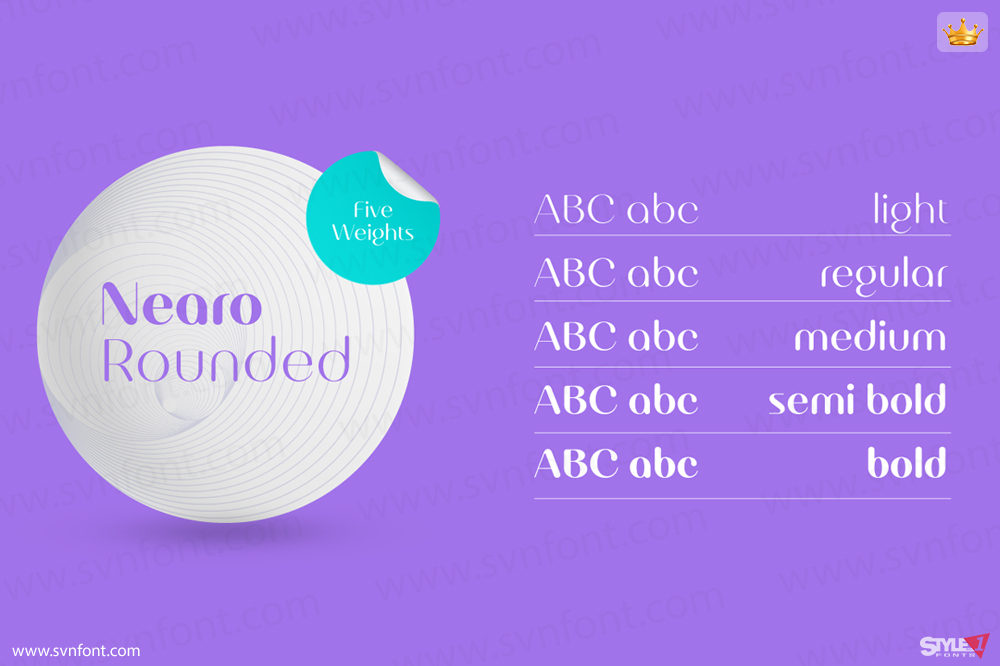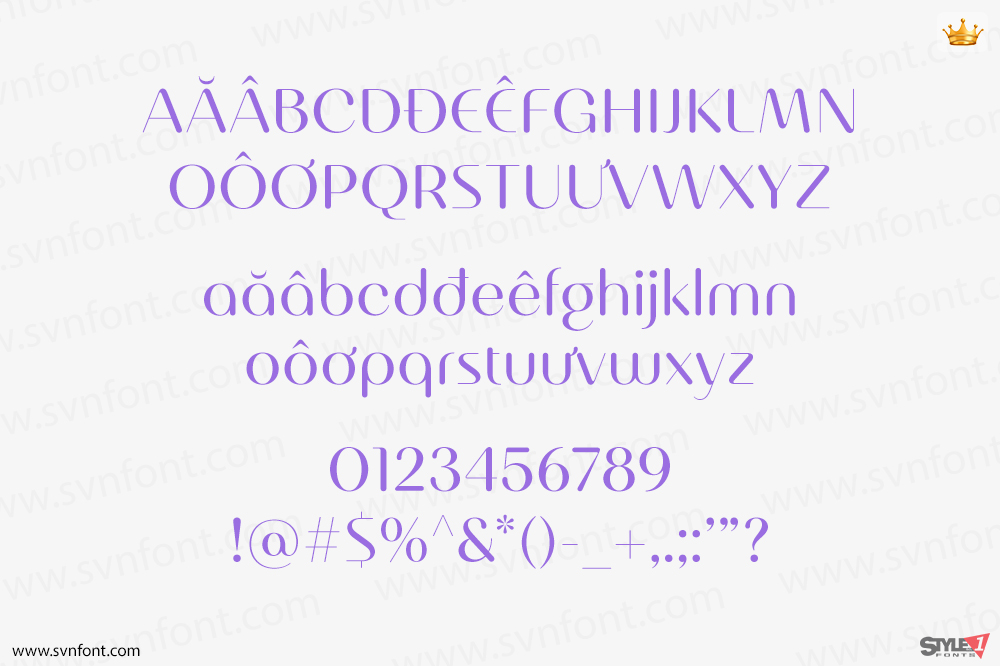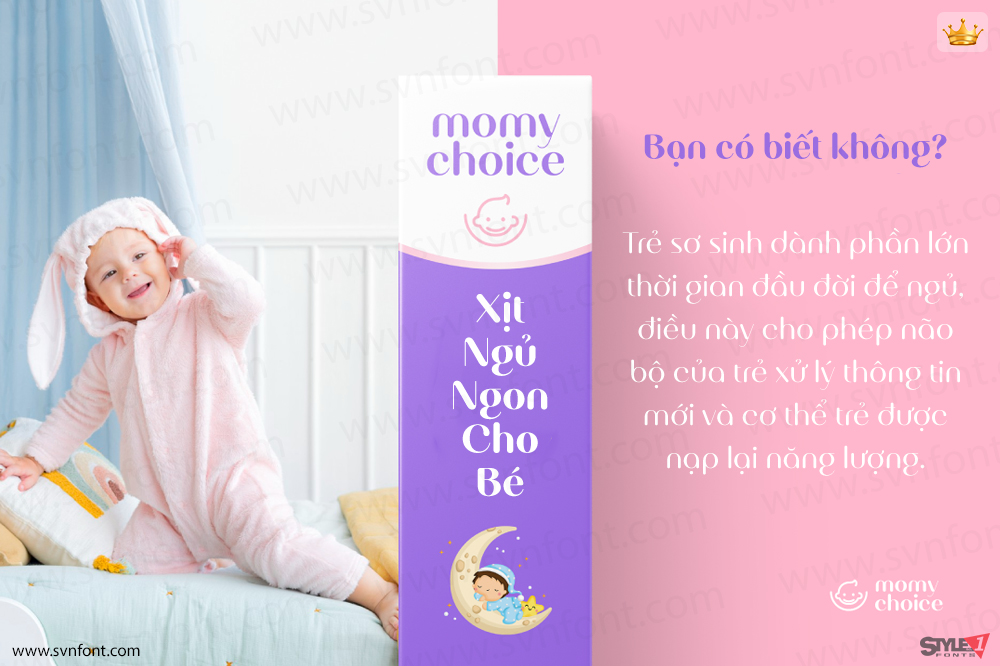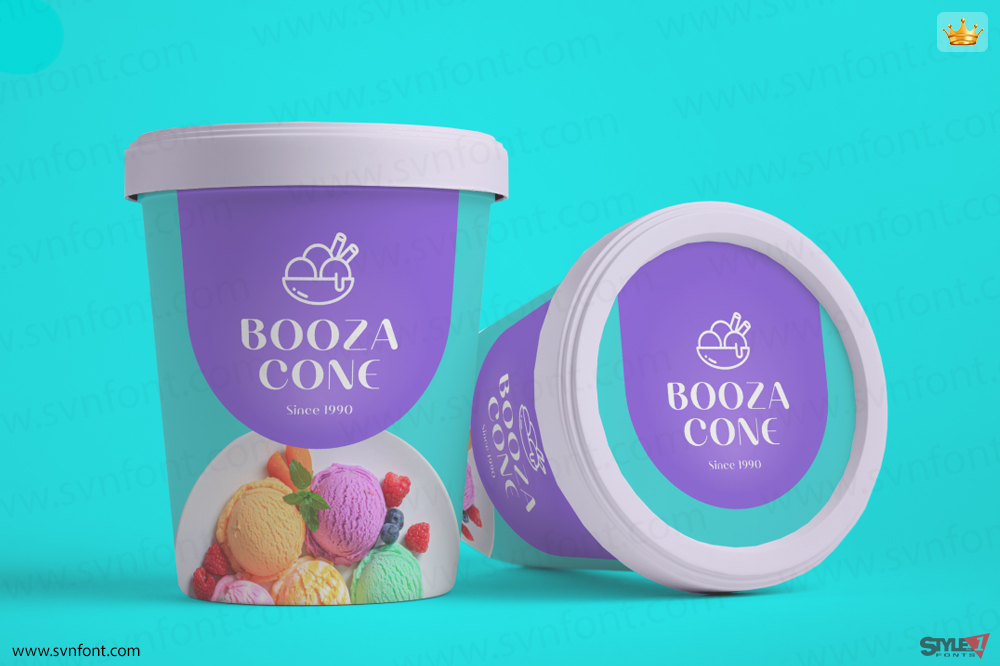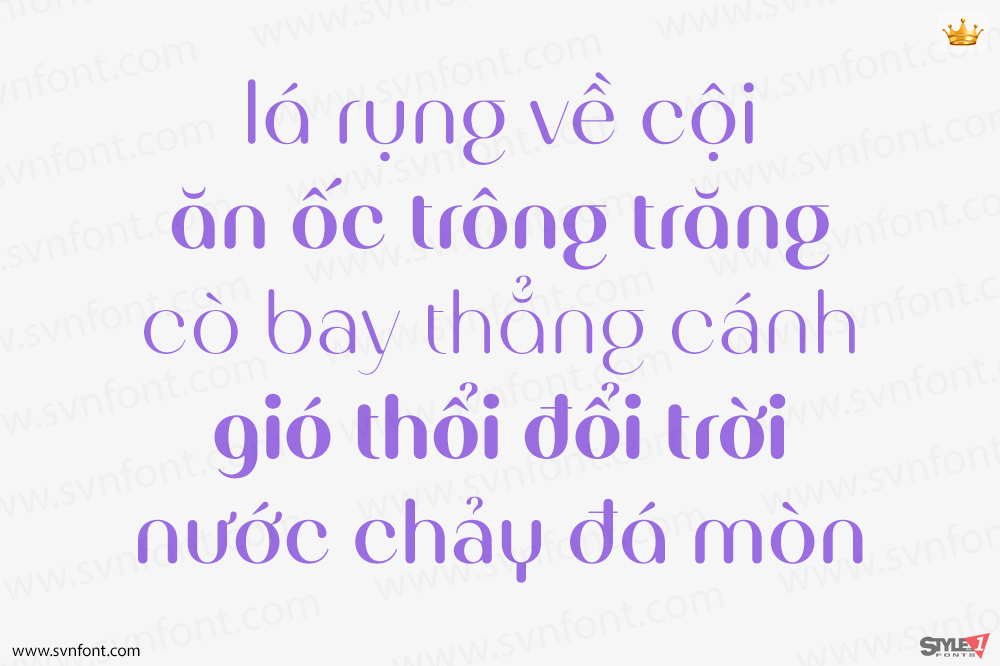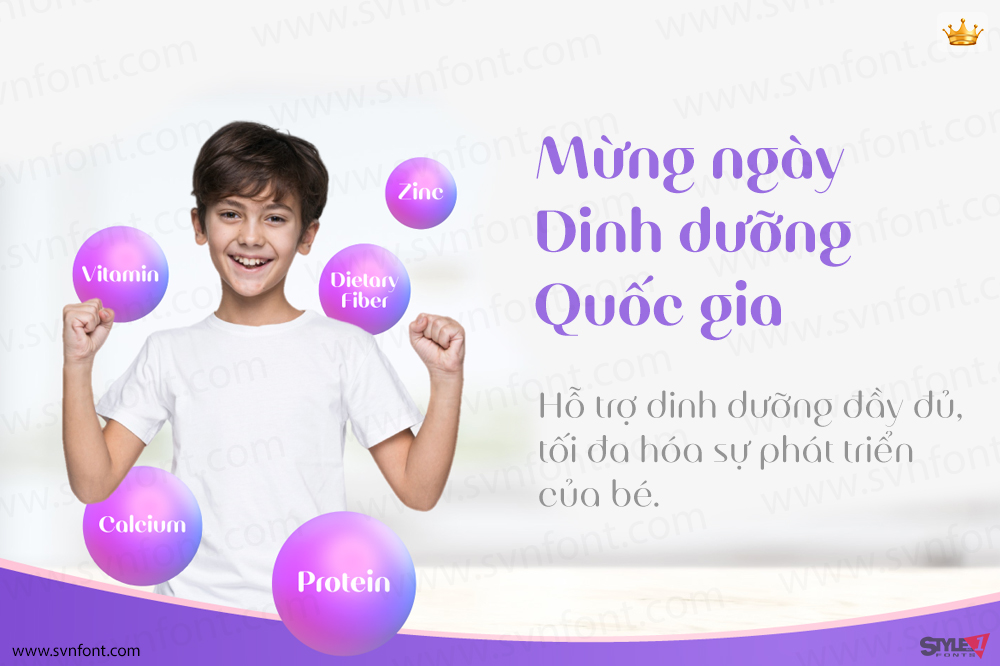
Nearo Rounded có năm kiểu chữ tương phản cao và các hình tròn dày mỏng, tạo nên sự độc đáo cho phông chữ này. Nearo Rounded có thể được ứng dụng vào nhiều dự án trang trọng khác nhau, bao gồm logo, tạp chí, sách, bao bì, thời trang, mỹ phẩm, thiệp mời, tiểu thuyết, nhãn mác, thiệp chúc mừng và các quảng cáo khác.